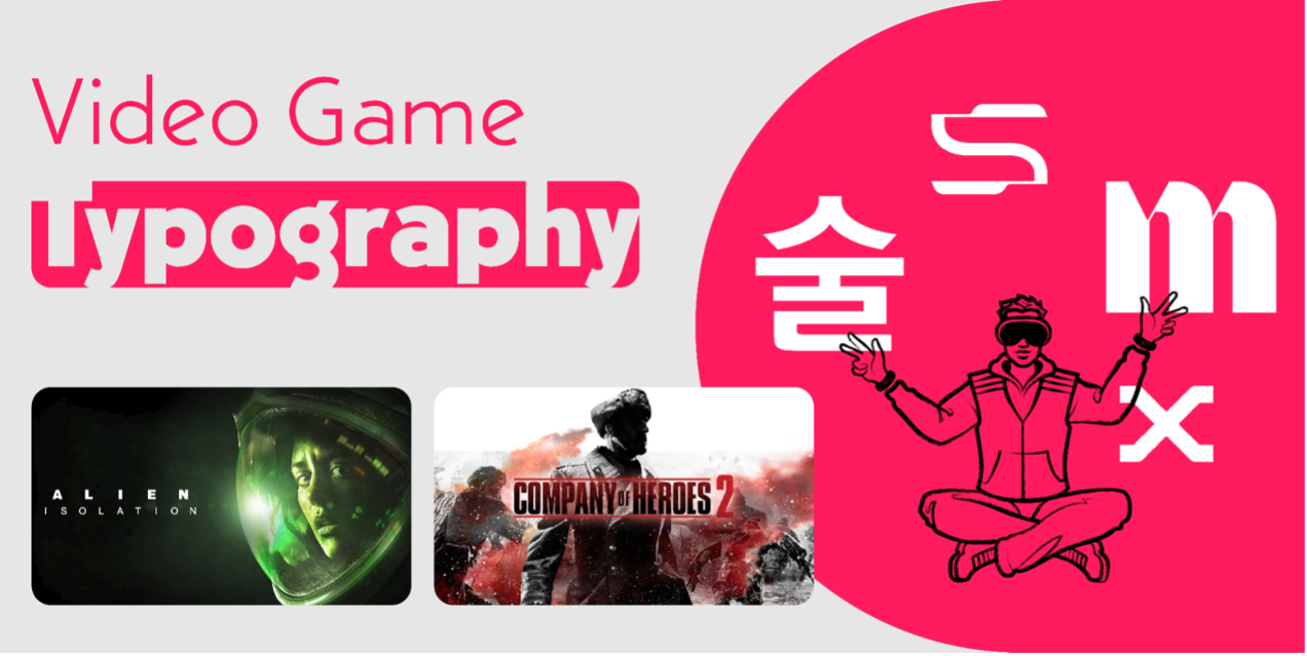
利用字体构建场景氛围,强化沉浸体验
字体作为视觉设计体系的重要构成,直接影响游戏世界观的具象化表达与情感传递效能。通过风格化字体的精准应用,可有效强化游戏场景的氛围感。例如,采用高对比度、多棱角的字形设计可增强恐怖题材游戏的压迫感;而圆润笔触、低饱和度的字体方案则能适配休闲类游戏的轻松基调。
这种视觉符号的系统性运用,能够引导玩家快速建立场景认知,深化剧情代入感,从而提升整体沉浸体验。
优化信息传递,塑造角色维度
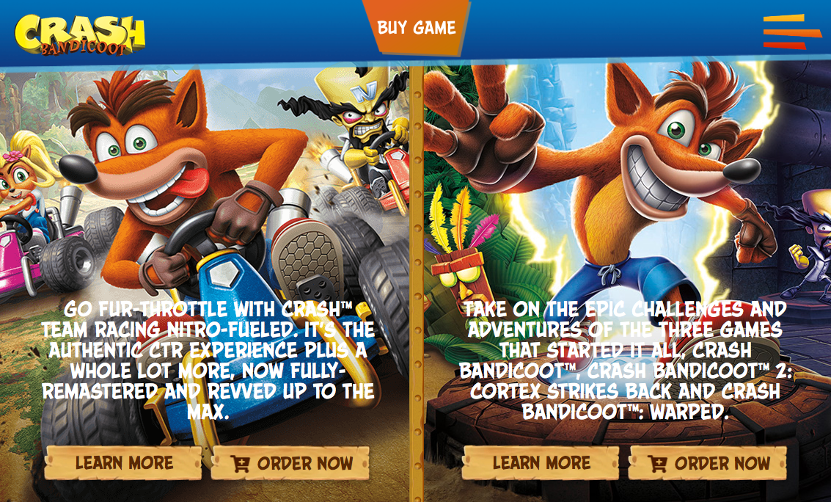
字体的易读性是游戏交互设计的基础指标,其直接决定信息传递的效率与准确性。在 UI 界面、剧情对话、任务指引等核心信息载体中,采用符合人体工学的字形结构与排版逻辑,可显著降低玩家的信息解码成本。
同时,字体设计可作为角色塑造的辅助手段:通过稳重的衬线字体强化英雄角色的权威性,以扭曲变形的字形凸显反派角色的非正统性,这种视觉符号的差异化应用,能够丰富角色的多维表达,增强玩家对角色特质的认知深度。
标准化导视系统,保障全球化体验一致性
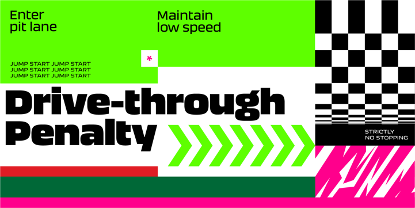
在复杂游戏场景中,字体是导视系统的核心视觉载体,其通过标准化的文字标识体系,实现对玩家行为的精准引导(如路标指示、任务提示等)。
统一的字体规范可确保导视信息的识别效率,减少玩家的认知负荷。对于全球化发行的游戏产品而言,字体的跨语言适配性与风格统一性更为关键。
通过构建标准化的字体应用体系,既能强化品牌视觉识别度,又能保障不同语言版本的用户获得一致的视觉体验,从而提升全球化运营的质量与效率。
蒙纳字库的游戏行业解决方案:艺术与技术的协同创新
作为全球领先的字体技术平台,蒙纳字库针对游戏行业需求,构建了涵盖 25 万余款多语种字体的资源库,并配套完善的技术支持体系,全面满足游戏开发中的美学表达与技术实现需求。
多元化字体资源与定制化服务
蒙纳字库的字体资源覆盖从传统风格到未来主义的全谱系设计,可适配各类游戏题材的视觉需求。同时,其具备成熟的定制化开发能力,已为 Garena 等头部游戏企业提供专属字体解决方案,助力游戏产品实现本地化表达的精准落地,提升海外市场的用户接受度。
全球化语言支持体系
依托覆盖数百种语言及字符集的字体资源库,蒙纳字库可为游戏的国际化运营提供全方位的语言适配支持,确保不同地区的用户均能获得符合文化语境的视觉体验,降低全球化推广中的文化隔阂。
在技术实现层面,蒙纳字库具备显著优势:
高兼容性:字体技术与 Unity 等主流游戏引擎及开发平台深度适配,确保在多环境下的无缝集成与稳定运行。
轻量化优化:通过字体文件压缩与渲染算法优化,在保证显示精度的前提下,显著降低内存占用与加载耗时,尤其适配移动端游戏的性能需求。
高精度字形微调(Hinting):采用先进的字形优化技术,确保字体在低分辨率设备及小字号显示场景下仍保持清晰的识别度,提升跨设备体验的一致性。
动态渲染技术:支持字体粗细、倾斜角度等参数的实时调整,为动态 UI、剧情动画等场景提供灵活的视觉表达能力,增强交互设计的层次感。
Web 端优化与开发工具链:针对网页端游戏场景,提供轻量化 Web 字体解决方案,通过资源压缩与加载策略优化,降低网络延迟。配套的字体子集生成工具可实现按需提取字符资源,进一步提升资源利用效率,简化开发流程。
目前,蒙纳字库已与腾讯游戏、Blizzard、Ubisoft、Riot Games、任天堂等全球知名游戏企业建立长期合作关系,其解决方案在众多爆款游戏产品中得到验证。